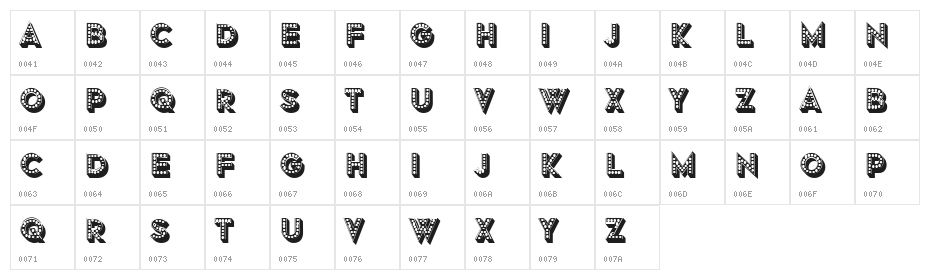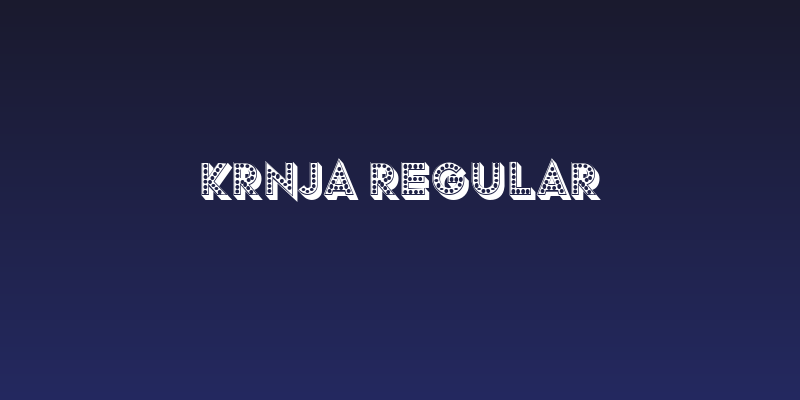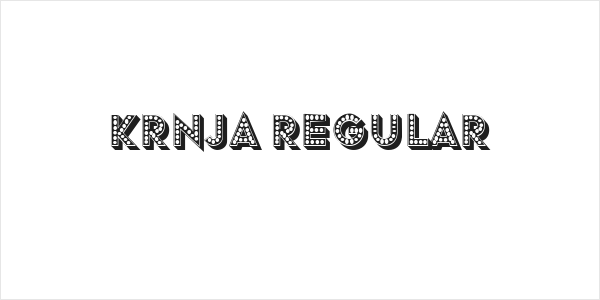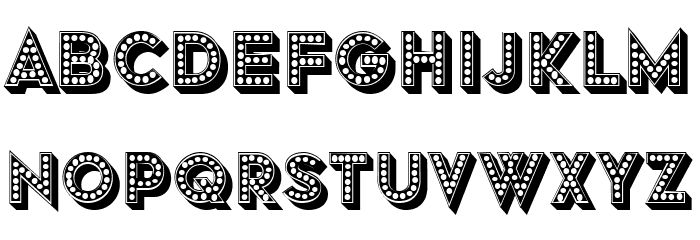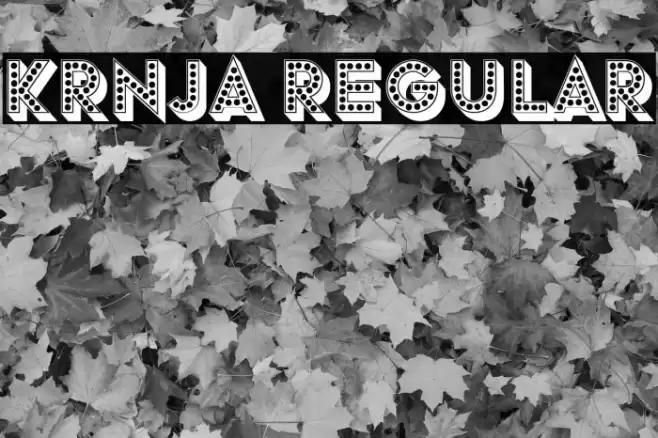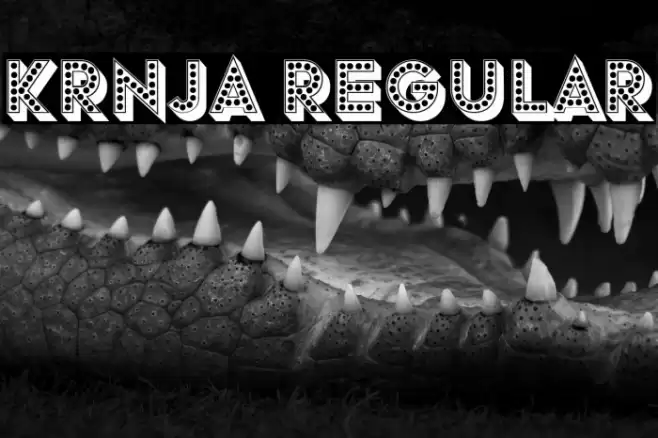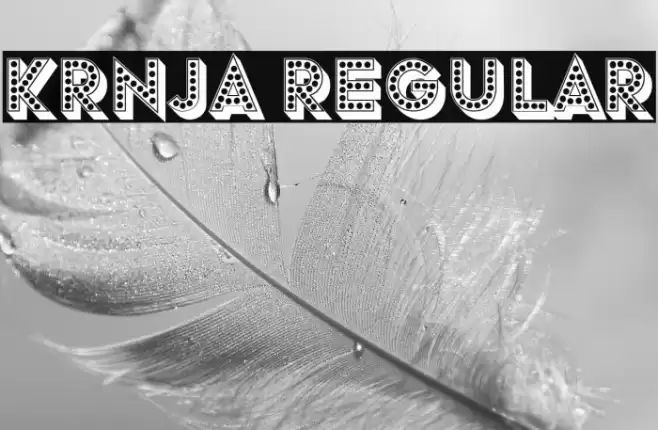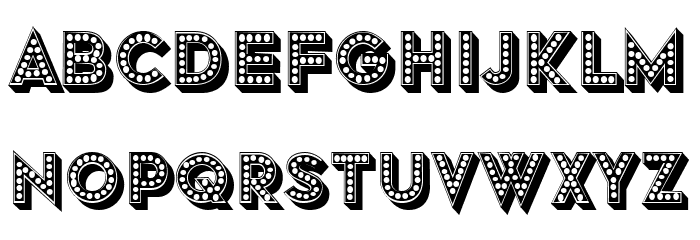
Krnja Regular Font
| Vorgeschlagene Projekte | Ideal for posters, event invitations, signage, and branding that require a dramatic and eye-catching style. |